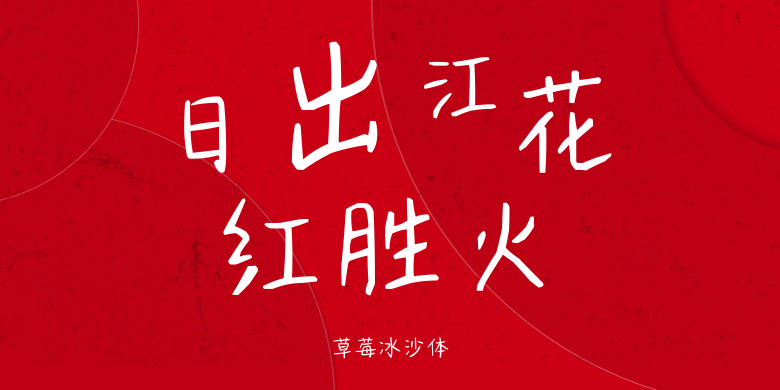
草莓冰沙体
草莓冰沙体,这款字体结构工整、笔画清晰,兼顾美观与易读性,适用于标题、正文、海报、包装、LOGO 等多种场景。字形优雅稳定,风格百搭耐看,适配日常排版与创意设计,让文字呈现更舒适、更具质感。草莓冰沙体一笔一画,皆是细节,以均衡的比例、流畅的线条打造舒适视觉体验,字形端正大气,风格简约现代。无论是商业设计、品牌宣传还是日常排版,都能轻松驾驭,让文字更有格调与力量。草莓冰沙体字体下载。